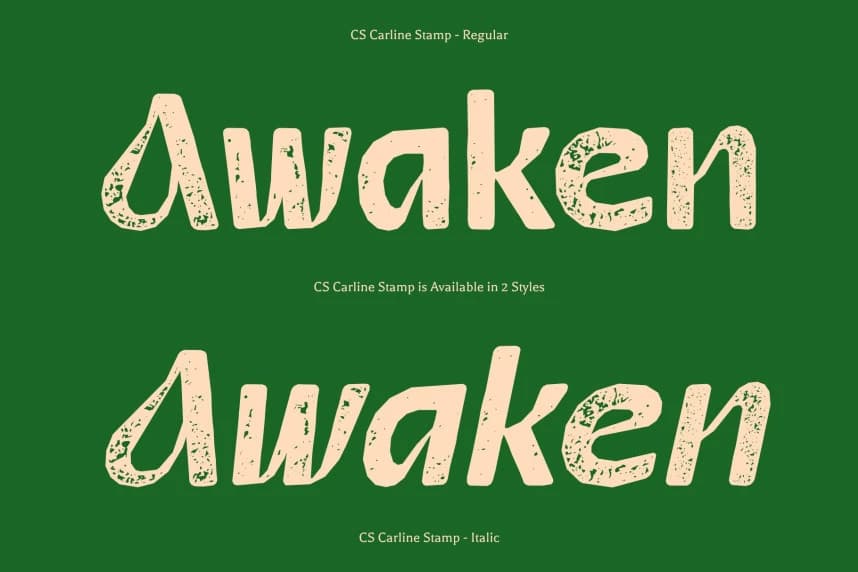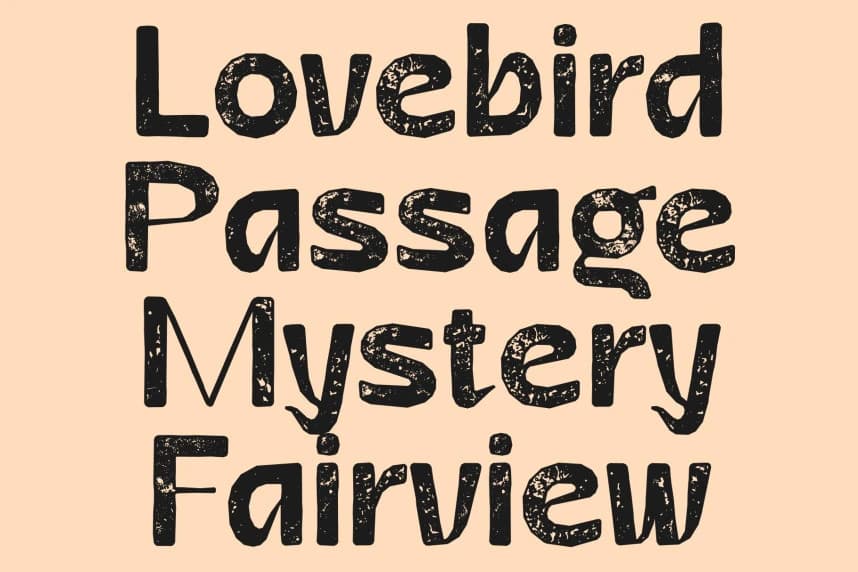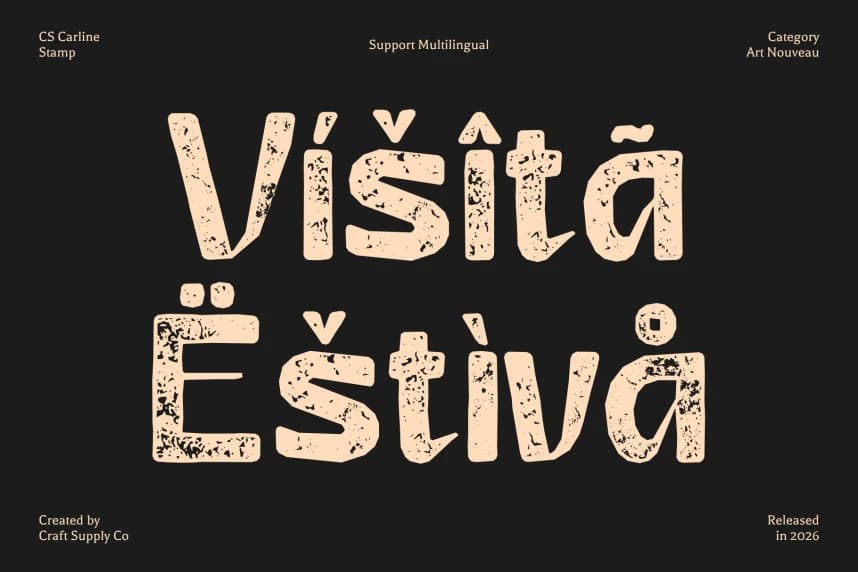
CS Carline Stamp Font
CS Carline Stamp Font – Vintage Doku ile Art Nouveau Zarafeti ve Dekoratif Art Nouveau Karakterli Zarif Kıvrımlar. Bu, Art Nouveau tasarımının akışkan güzelliğinden esinlenen modern bir sans-serif yazı tipidir.
CS Carline Stamp Font – Vintage Doku ile Art Nouveau Zarafeti, Dekoratif Art Nouveau Karakterli Zarif Eğriler. Bu, Art Nouveau tasarımının akışkan güzelliğinden ilham alan modern bir sans-serif yazı tipidir.